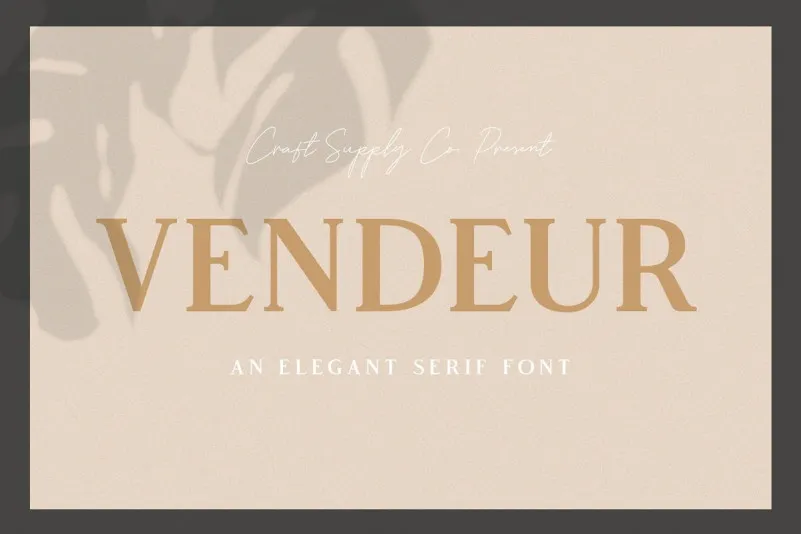
Vendeur Serif Font – Download Grátis
Vendeur Serif é uma fonte elegante do tipo serif que certamente trará seu projeto para a frente. Desenvolvida por Daikian, esta fonte possui traços robustos e delicada simplicidade feminina, adequada tanto para projetos modernos quanto para design minimalista. Seu estilo contemporâneo se torna ainda mais notável graças aos traços de menor contraste e formas arredondadas que lembram a simplicidade profissional e ao mesmo tempo têm uma personalidade vibrante. Vendeur é ideal não apenas para projetos artísticos, mas também para letras de cartas modernas em envelope, desenhos manualizados, temas de arte aquatélica ou qualquer projeto DIY. Eles são perfeitos para títulos de livros e até mesmo para fontes de casamento vintage, trazendo um toque de elegância aos projetos que vão desde a arte tradicional até as tendências da moda moderna. É uma escolha inteligente para designers que buscam deixar uma impressão com suas criações. Com Vendeur, os criadores podem expressar seu estilo e habilidade de maneira única, sem perder o aspecto sofisticado e elegante do tipo serif. A fonte oferece inúmeras possibilidades para criar designs atraentes e trendy, garantindo que o projeto em questão brilhe através da escolha certa de uma fonte.